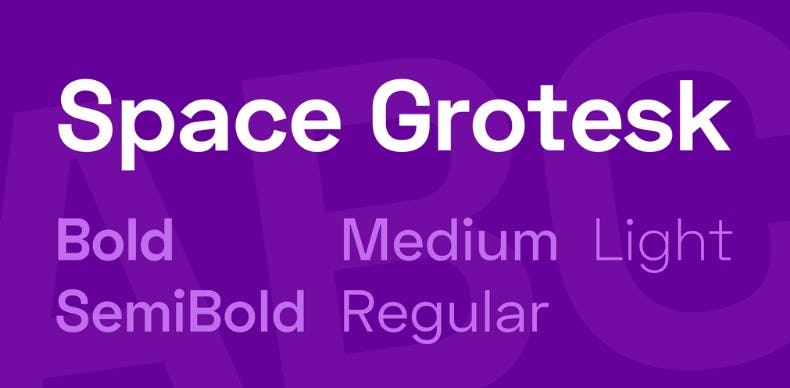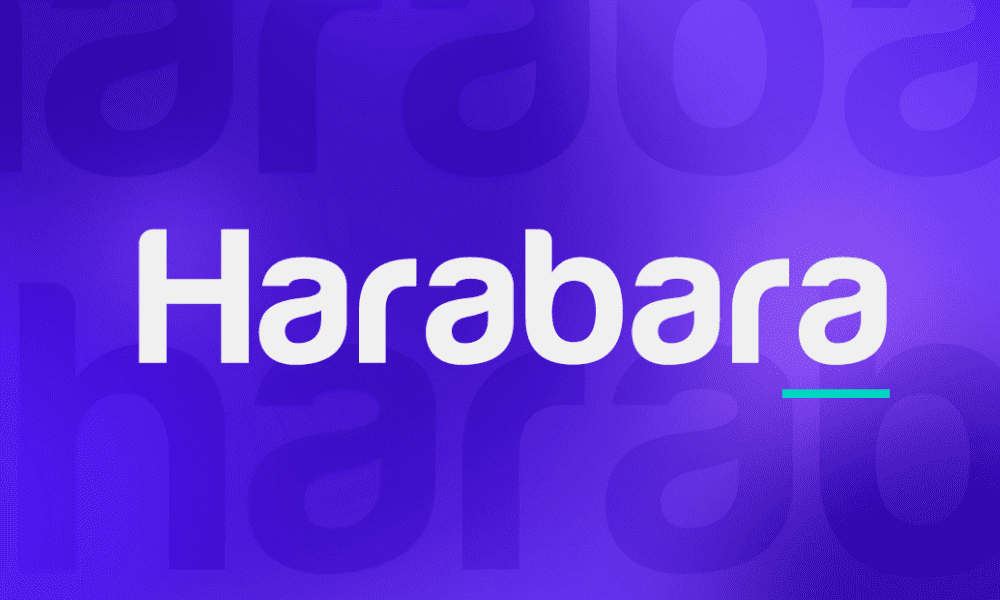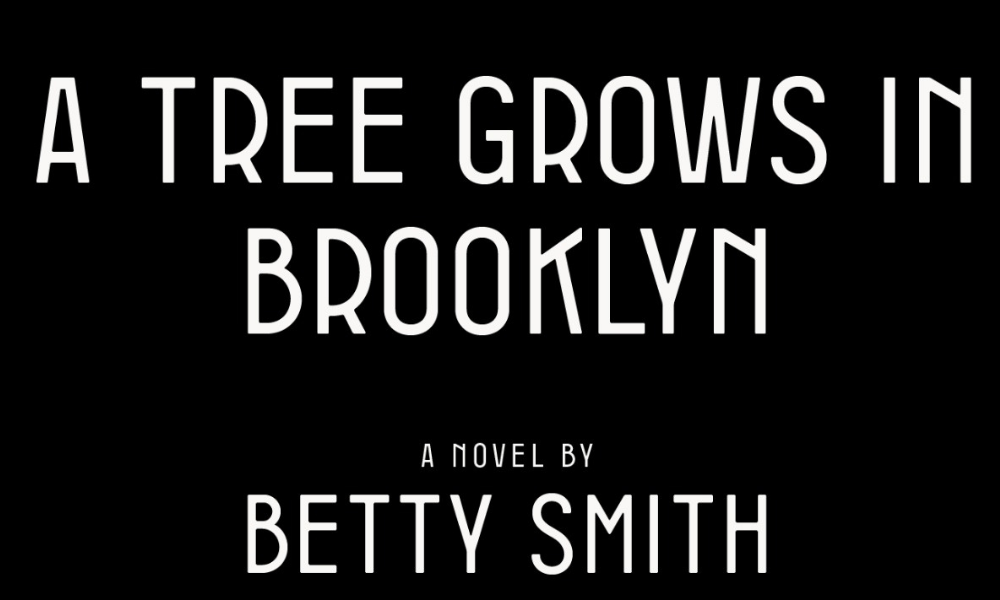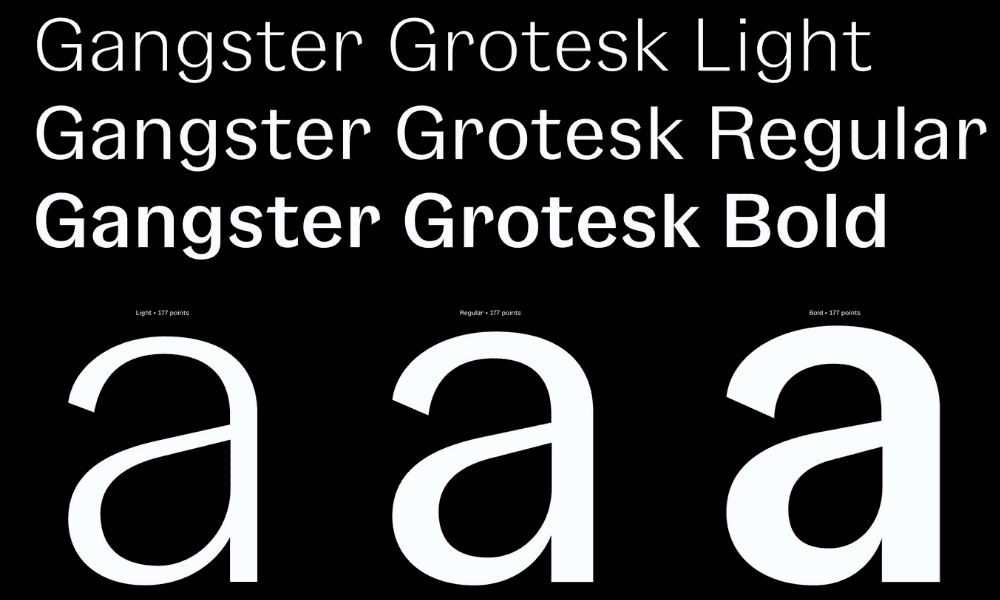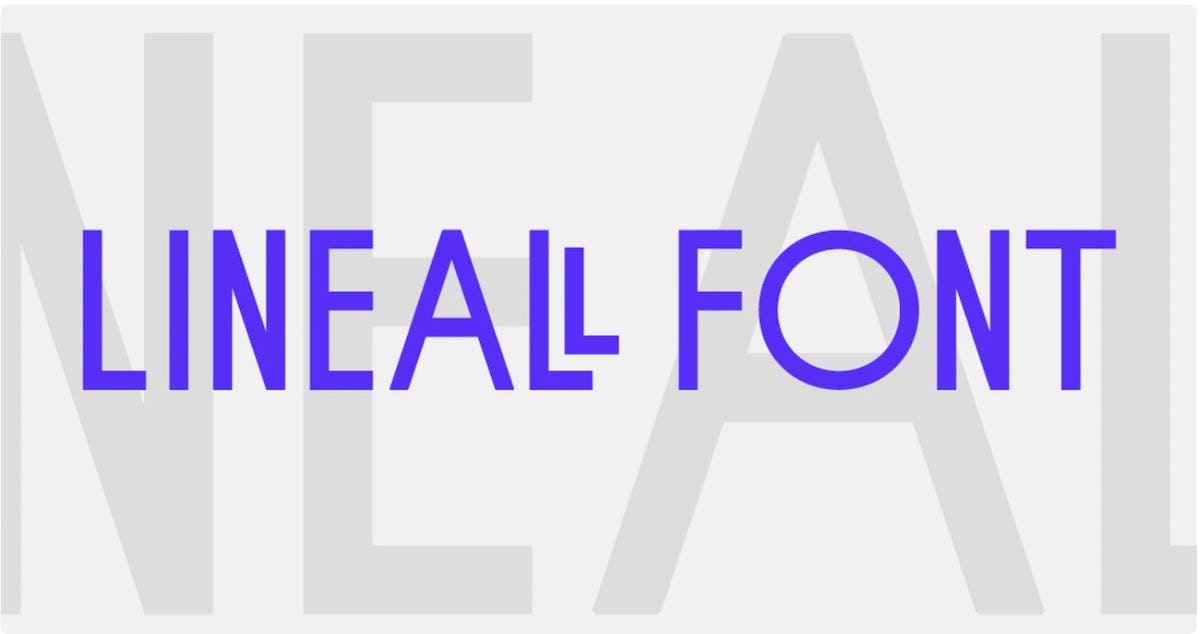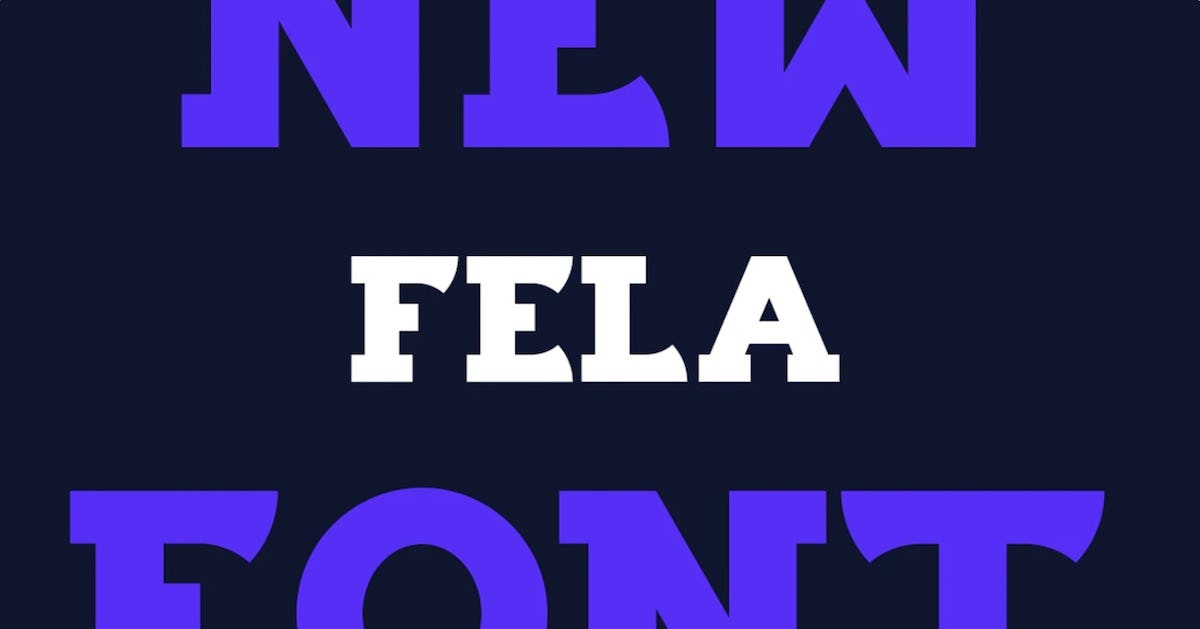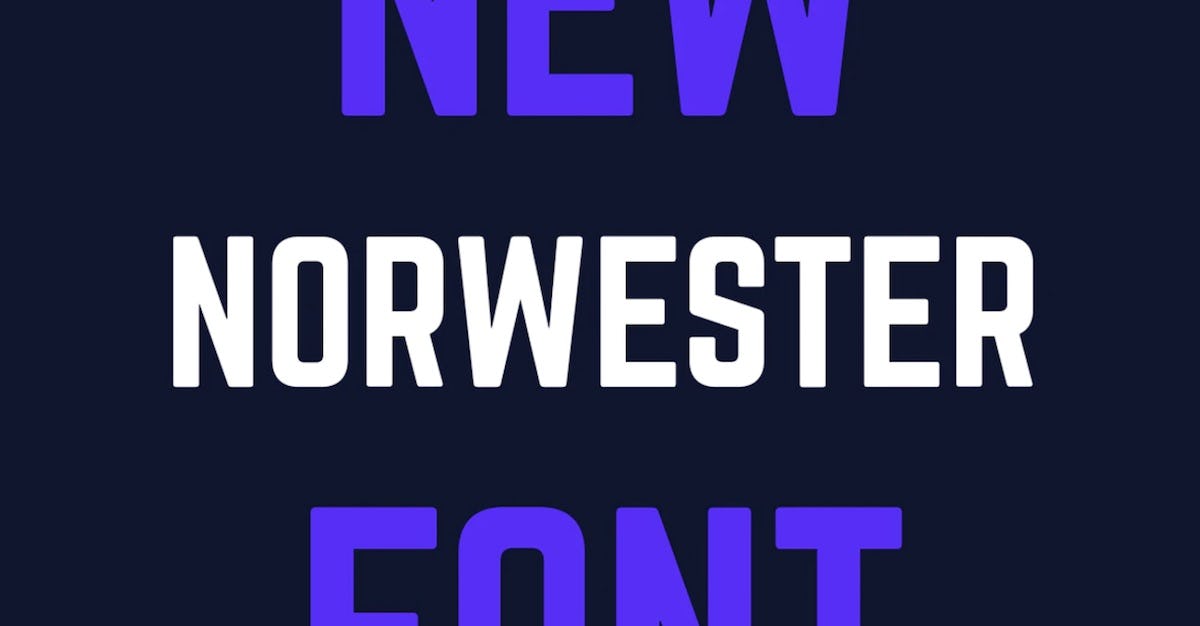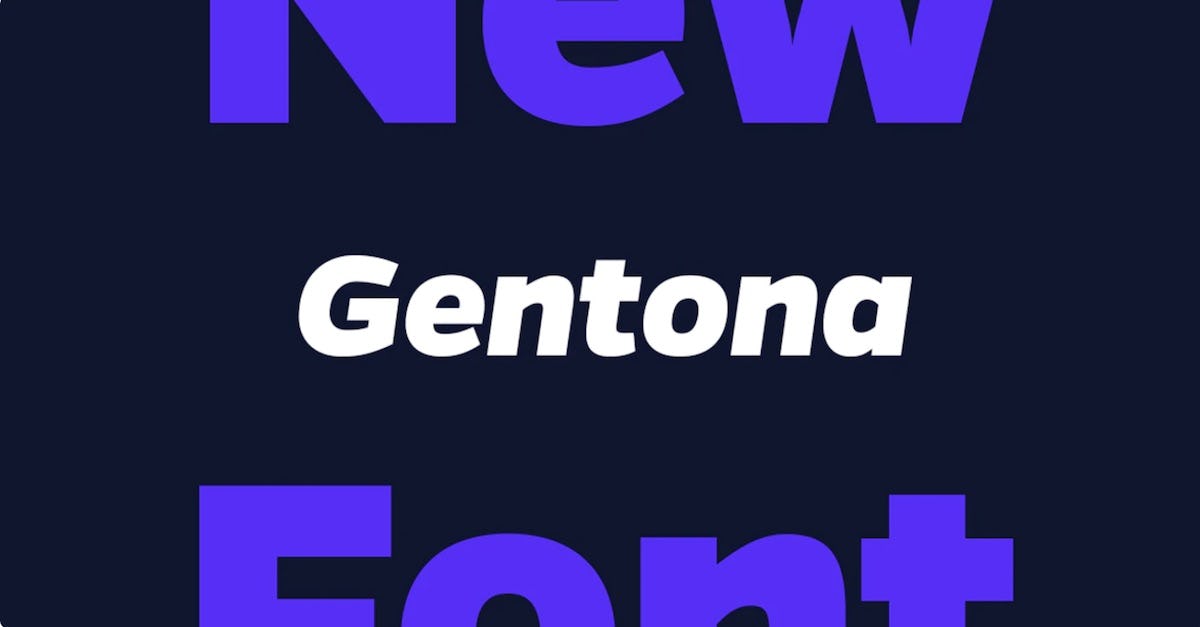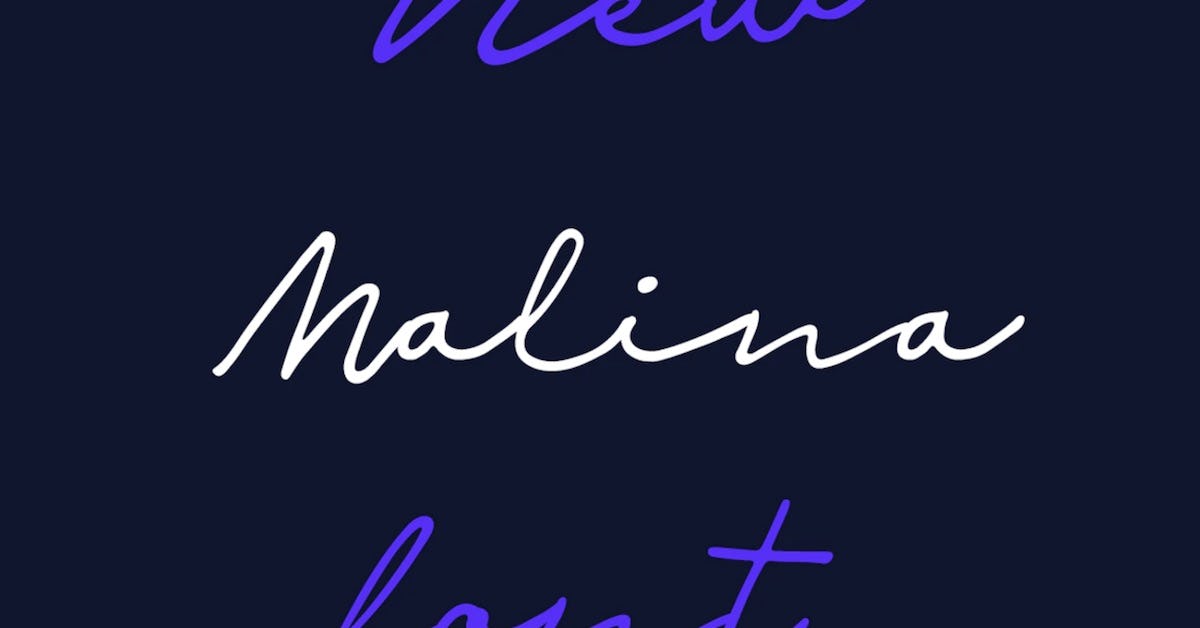
Las tipografías para infografías constituyen un recurso, que como diseñador gráfico, debes conocer para comunicar con precisión y cautivar a tus clientes. La palabra “infografía” proviene del inglés “information graphics” y ha sido ampliamente utilizada en distintos ámbitos de comunicación. Las primeras infografías han aparecido dentro de contextos periodísticos y editoriales; para luego, expandirse al resto de los soportes de comunicación visual.
Por eso, hemos preparado esta lista con las +15 tipografías para infografías que darán un look cool a tu diseño. Y como consecuencia, la información combinada con imágenes en cada una de las infografías, hará que tus proyectos creativos luzcan perfectos.
1. Streetwear Free Font: una fuente tipográfica legible
Esta es una de las tipografías para infografías más usadas en el mundo del diseño. Por eso, si tu objetivo es encontrar fuentes para títulos de infografías, descargar Streetwear es una buena opción. Según sus creadores, este tipo de letra para infografía es de inspiración “retro audaz y elegante”. Además, si tienes que hacer una presentación que evoque a las décadas del sesenta o setenta, esta tipografía para infografías es ideal.
Así, el estilo y presencia de Streetwear convierten a esta tipografía para infografías en un tipo de letra con una fuerza e impacto necesarios, para lograr la identidad visual de una empresa. Así que esta tipografía Streetwear es mucho más que una fuente para títulos de infografía.
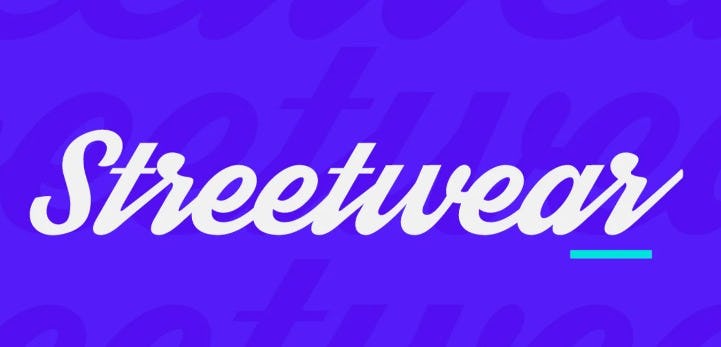
Al mismo tiempo, este tipo de letra es una de las tipografías para logos más elegidas a la hora de emprender un diseño de branding integral para una compañía. Es que hoy en día, las infografías se solicitan dentro de campos de trabajo muy diversos, que incluyen por supuesto, el marketing digital para generar mayor cantidad de tráfico hacia los distintos sitios en línea.
- Una vez que sepas a quién te diriges, cuál es tu objetivo y qué datos compondrán tu infografía, es momento de definir el estilo. Aquí, es cuando debes optar por cierta paleta de colores, símbolos, tamaños y elegir la tipografía para infografías entre los diversos tipos de letras. La elección del tipo de letra para una infografía es importante y no deberías dejarlo como último elemento. ¿Por qué? Porque la fuente de las letras de tu texto es la que transmite el mensaje. De hecho, contiene el elemento que permitirá la comprensión o refuerzo de lo que quieres comunicar. Por último, recuerda que este tipo de decisiones debes tomarlas de acuerdo al canal de comunicación por el cual circulará la infografía.
2. Lineal Font: otro diseño de letra ideal para tus infografías
Si decides descargar Lineal, tomarás una buena decisión, ya que es una de las mejores tipografías para infografías por la claridad de su diseño. Los trazos rectos y de llamativo grosor hacen que pueda ser utilizada como un excelente tipo de letra para infografía.
Fuente: Crehana
Según información dada por el diseñador de esta tipografía, Lineal está inspirada en la canción “2870” de Gérard Manset. El creador de esta tipografía recomendada para infografías es Frank Adebiaye; y su el estilo tiene un poco de geométrico, sans serif y brutalista. De hecho, este diseño de letra asemeja una caja de gran altura; y seguramente, a través de sus ligaduras excéntricas, podrás llamar la atención de todos tus lectores de infografías.
A la vez, esta tipografía para infografías es una fuente de código abierto. Esto quiere decir que puedes modificar y redistribuir el tipo de letra libremente.
3. Fela Free Font: una tipografía para infografías armónica
¿Quieres usar una fuente negrita para tu presentación? Si es así, descarga Fela Free Font, ya que es el tipo de letra para una infografía que llama mucho la atención. Los trazos gruesos aseguran que la frase escrita con esta tipografía para infografías sea la primera que se lleve la atención de tus lectores.
Esta fuente tipografía fue diseñada por Laszlo Feja y es de los mejores tipos de letras para infografías. Además, otra ventaja adicional es que Fela Free Font tiene licencia libre; y por lo tanto, puedes usarla a nivel personal y comercial. ¿No es fantástico?